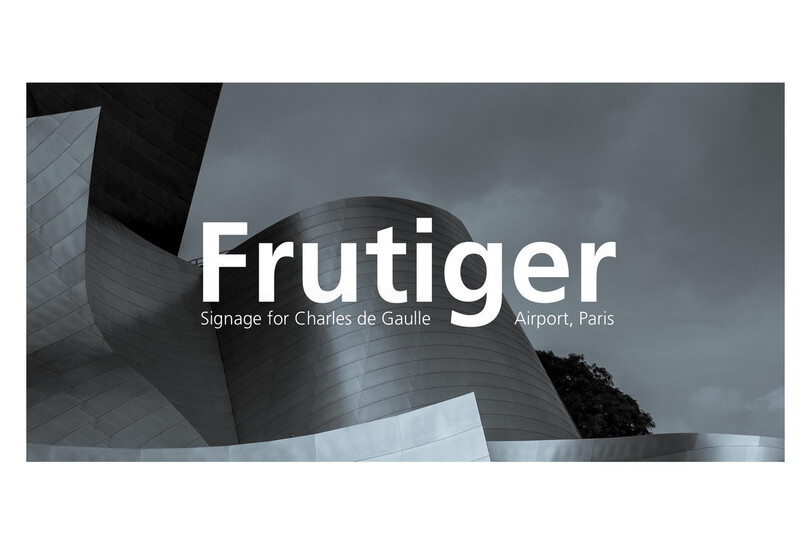
Pourquoi les marques adorent les polices sans serif (et comment choisir la vôtre).
“ Nous constatons encore aujourd’hui les conséquences de l’arrivée d’internet et des réseaux sociaux sur l’économie mondiale, mais aussi sur les idéaux et les attitudes des marques. ”
Sans
Sujet
Lorsque les polices sans serif (dénuées d’empattement) ont débarqué dans les ateliers de typographie au début des années 1900, ce n’était pas juste par effet de mode, mais bien pour rester. Découvrez comment choisir celle qui correspond à votre marque.
Un peu d’Histoire…
En 1816, William Caslon IV conçoit Caslon, la première police de caractères sans serif qui, à l’époque, ne reçoit pas un accueil très populaire. Cependant, lorsque le modernisme émerge au début du siècle dernier, la conception design des formes se met à suivre la fonction, et l’utilisation des polices sans serif explose.
S’inspirant des machines modernes et de la production de masse, le modernisme s’est construit sur les concepts d’efficacité, de structure et de simplicité. Avant cela, le design graphique était élaboré et ornementé. Le modernisme a mis l’accent sur l’uniformité, la géométrie et les espaces vides. Les lignes fluides et épurées ont supplanté les éléments décoratifs qui n’existaient que pour embellir, car les designers ont exploré l’utilisation de l’espace négatif et des formes de caractères lisses. Le design se veut alors pratique et utile.
C’est à l’apogée du modernisme (1920-1970), que certaines des polices sans serif les plus populaires et les plus reconnues sont créées : Futura, une géométrique sans, Helvetica et Univers, des néo-grotesques sans et Frutiger, une humaniste sans. (Pour en savoir plus sur la classification des polices, cliquez ici.)
Frutiger
Il n’est donc pas surprenant que les industries en plein essor aient vivement compté sur ce nouveau style épuré. Une police sans serif est synonyme de progrès et met l’accent sur l’avenir. C’est pourquoi, très tôt, les entreprises aérospatiales, technologiques, médicales et biotechnologiques ont adopté les sans serif. Et avec la multiplication actuelle du nombre d’entreprises technologiques, les polices sans serif continuent de dominer pour cette même raison.
Lorsque sont apparus les écrans numériques de petite taille, les polices sans serif ont été privilégiées pour améliorer la lisibilité. La résolution était alors médiocre et il fallait abandonner les empattements pour que le rendu des caractères soit net. L’arrivée des écrans à haute résolution a aujourd’hui supprimé la nécessité des polices sans serif pour clarifier la lisibilité, mais la plupart des marques continuent à préférer une sans serif en police principale.
Le sans serif aujourd’hui
Les marques modernes n’ont jamais eu aussi peu de temps pour créer un lien avec leur public. Pour cette raison, elles tentent d’imaginer les messages les plus séduisants, les plus accessibles et les plus digestes possible. Comme les gens sont inondés de messages commerciaux, ils filtrent ce qui leur plaît le plus et ignorent les marques qui ne réussissent pas à les impliquer personnellement. On comprend bien pourquoi les idéaux modernistes majeurs tels que simplicité et efficacité prévalent, et pourquoi les sans serif sont plus répandus que jamais.
Univers
De nombreuses marques contemporaines souhaitent aussi être considérées comme avant-gardistes, audacieuses, actuelles et même jeunes. Les polices sans serif connotent la modernité et l’innovation et participent à renforcer ces perceptions, et, puisque le public, les médias et le marché évoluent constamment, les marques ne veulent pas être laissées sur le bord du chemin.
« Nous constatons encore aujourd’hui les conséquences de l’arrivée d’internet et des réseaux sociaux sur l’économie mondiale, mais aussi sur les idéaux et les attitudes des marques », déclare Terrance Weinzierl, designer typographique senior chez Monotype. La culture a indéniablement évolué et cela a mené les marques à repenser qui elles sont et comment elles veulent se présenter.
Dans le cadre de cette évolution, les polices sans serif sont un choix design pratique. Les lignes nettes et les espaces vides s’adaptent parfaitement à de nombreux styles et approches, ce qui les rend très adaptables à de nombreuses sortes de médias - grands ou petits, imprimés ou numériques, statiques ou animés.
« Prenez Helvetica, par exemple », explique Weinzierl. « [La police est] utilisée par Target, Gap et American Apparel. Pouvez-vous faire la différence entre les titres écrits pour ces entreprises ? Peut-être reconnaîtrez-vous leur style de rédaction. Et la photographie ? Parfaitement. La couleur ? Bien sûr. La façon dont une marque utilise une police de caractères avec d’autres éléments de design a un impact considérable sur l’état d’esprit et le message exprimés. Des marques très différentes peuvent utiliser la même police dans des styles très différents et avoir des résultats très différents. »
Helvetica
Parmi les exemples de marques ayant choisi des polices sans serif on peut citer Remax et le Prix Nobel. Remax est passée d’un style géométrique sans à un autre et le Prix Nobel a opté pour une nouvelle police et de nouvelles couleurs de marque soulignant l’aspect intellectuel, l’équilibre et le sérieux de l’organisation.
Il conclut : « Nous verrons l’arrivée de polices variables avec des tailles optiques, c’est-à-dire une police qui fonctionne partout où les marques auront besoin d’elle. Peut-être verrons-nous aussi des polices qui évoluent selon la distance de lecture en réalité virtuelle ou des animations qui suivent les mouvements et l’accélération, ou encore des polices qui s’adaptent automatiquement pour être utilisées dans différentes tailles. »